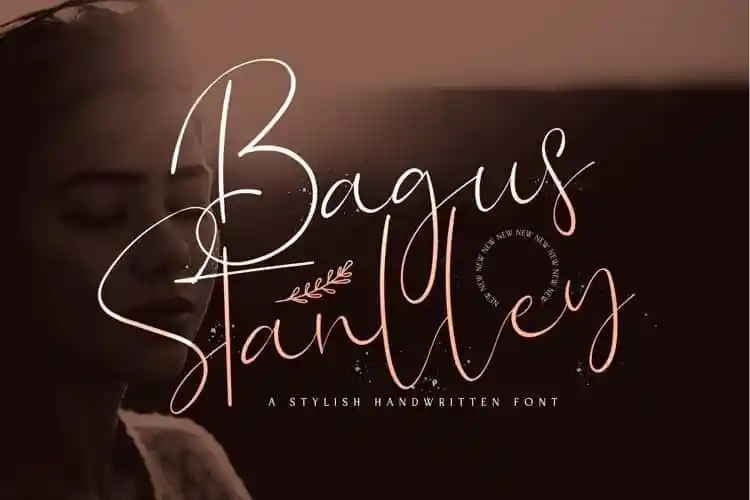
Bagus Stanlley Script Font – Fonte Grátis
Bagus Stanlley Script Font
Introduzimos Bagus Stanlley Script Font, uma fonte com estilo de assinatura escrita a mão. Esta elegante fonte mantém um aspecto desajeitado e casual, complementada por ligaturas que promovem o fluxo da sensação de escrita humana em seus projetos. Com seu design clássico incrivelmente refinado e ainda mantendo uma atmosfera agradável, Bagus Stanlley Script Font é perfeito para aqueles que desejam um toque pessoal em suas criações digitais. O fato de ser PUA (Propriedade Unicode Associada) codificado significa que você pode facilmente acessar todos os caracteres divertidos e acrobatas com apenas alguns cliques. Além disso, a fonte oferece uma ampla gama de recursos especiais como alternativas de letras e ligaturas, adicionando ainda mais personalização para seu design. Esta é a escolha perfeita para aqueles que buscam um toque único e emocionante em seus projetos digitais.